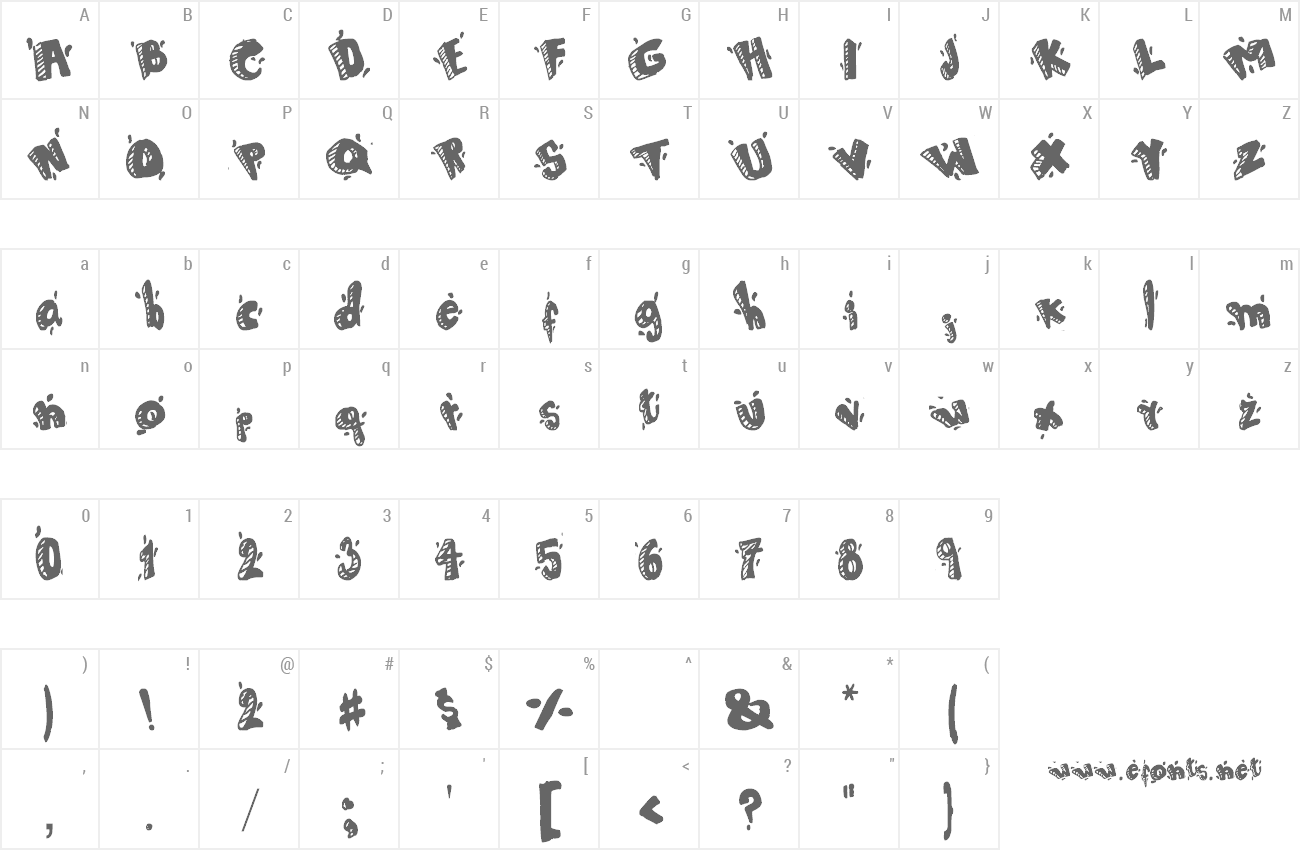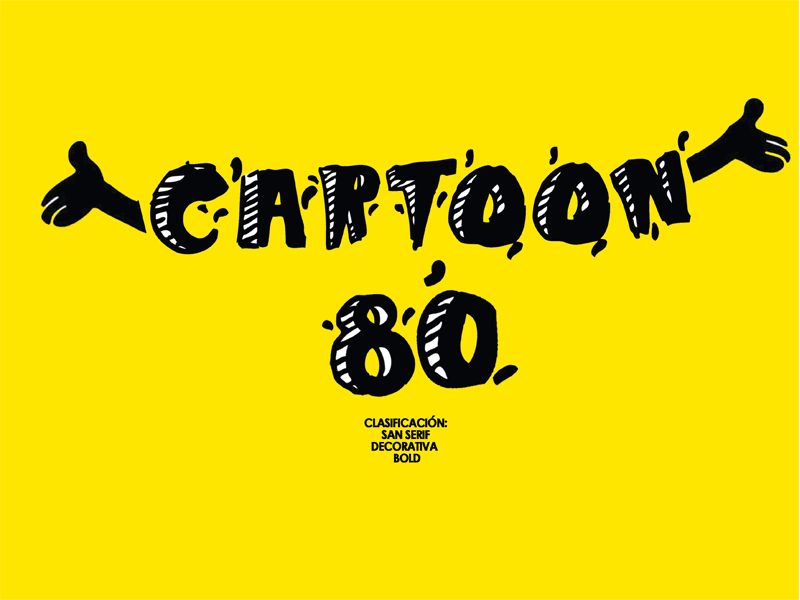
| espero que las disfrutes gracias por usar mis tipografías créeme no fue tarea fácil crearlas estas tipografías esta inspirada en aquellas caricaturas viejas de los años 80 y en especial en felix el gato son perfectas para el uso en carteles o como aplicación en camisetas etc disfrútalas |